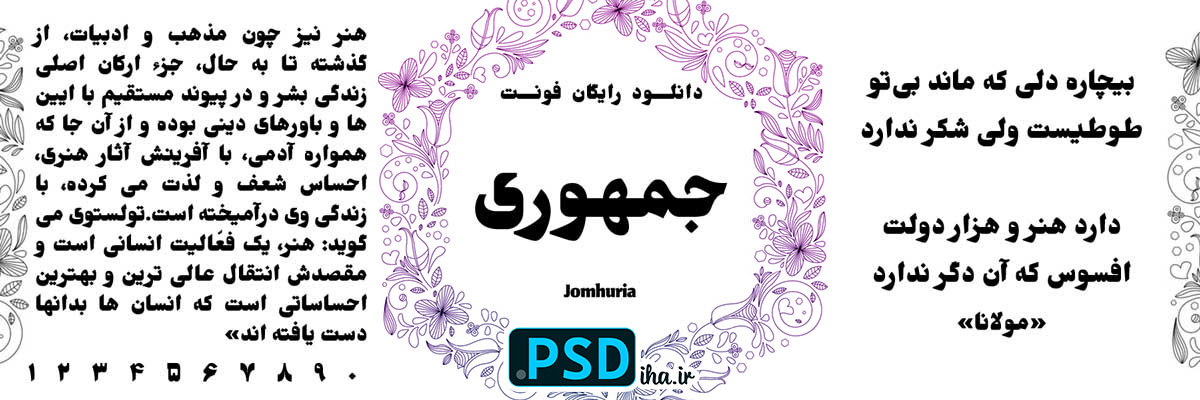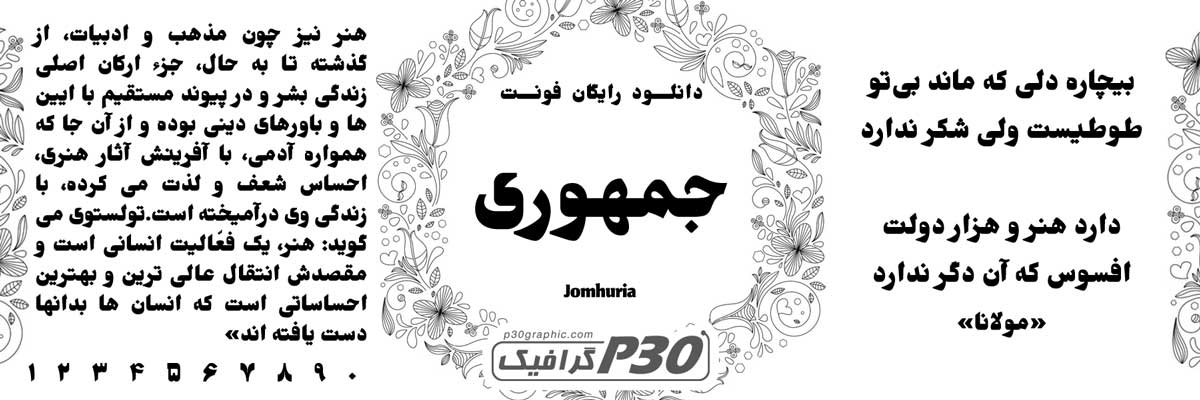
دانلود فونت جمهوری رایگان
فونت جمهوری
تو دنبال تیترهایی می‌گردی که مثل یه مشت محکم، توجه مخاطب رو جلب کنن؟ دانلود فونت جمهوری رایگان رو از دست نده. من تو پروژه‌های چاپی‌م، از بنرهای انتخاباتی تا کارت‌های ویزیت شرکتی، بارها از این فونت bold استفاده کردم. هر بار، طرح‌م یه نفس تازه می‌کشه. طراحی زیباش، با ضخامت جسورانه و خطوط صاف، از روحیه انقلابی و مدرن ایران الهام می‌گیره. این فونت تیترها رو فوری برجسته می‌کنه. تصور کن تیتر یه تراکت تبلیغاتی یا لوگوی برندت با جمهوری. مخاطب‌ها چشم برنمی‌دارن، چون قدرتمنده و ظریف.
چرا فونت جمهوری برای تیترهای چاپی بی‌رقیبه؟
فونت جمهوری وزن bold اختصاصی داره. این وزن تو عناوین می‌درخشه. خوانایی‌ش تو اندازه‌های بزرگ عالیه. تو چاپ، لبه‌ها و رنگ‌ها مثل پرچم تند و تیز زنده می‌مونن. طراحان ازش برای تراکت‌های تبلیغاتی، کارت‌های ویزیت برجسته، لیبل‌های محصولات قدرتمند و پوسترهای رویدادی استفاده می‌کنن. با فتوشاپ یا ایلاستریتور، بدون مشکل کار می‌کنه. تو چاپ نهایی روی کاغذهای گلاسه یا مات، حس قدرت‌ش دوچندان می‌شه. یادمه پروژه کارت ویزیت برای یه استارت‌آپ داشتم. تیتر bold با جمهوری، طرح رو از معمولی به افسانه‌ای برد. مشتری حالا سفارش‌های بعدی‌ش رو به ما می‌ده!
فونت جمهوری روی زیبایی bold تمرکز داره. انحناهای ملایمش جذابیت می‌ده. ضخامت‌ش تأکید می‌کنه. با متن‌های فارسی سازگاره. تیترهات رو نه تنها دیده می‌کنه، بلکه الهام‌بخش می‌کنه. این فونت بهترین هم‌تیمی‌ته!
نکته کلیدی: برای تیترهای bold، فاصله حروف رو تنظیم کن (کرنینگ). تو چاپ واقعی، تعادل‌ش بیشتر می‌شه. من همیشه این کار رو می‌کنم. نتیجه‌ش عالیه.